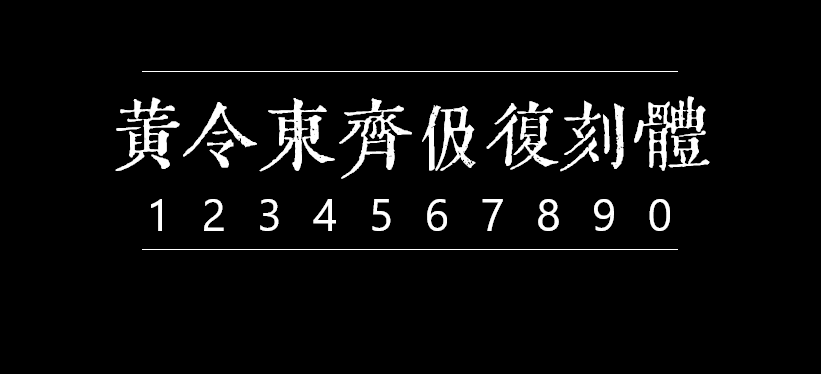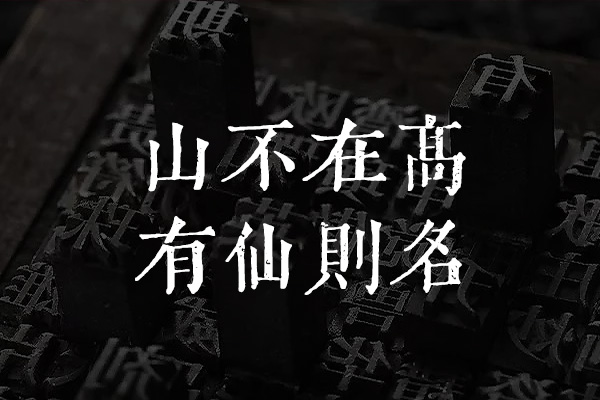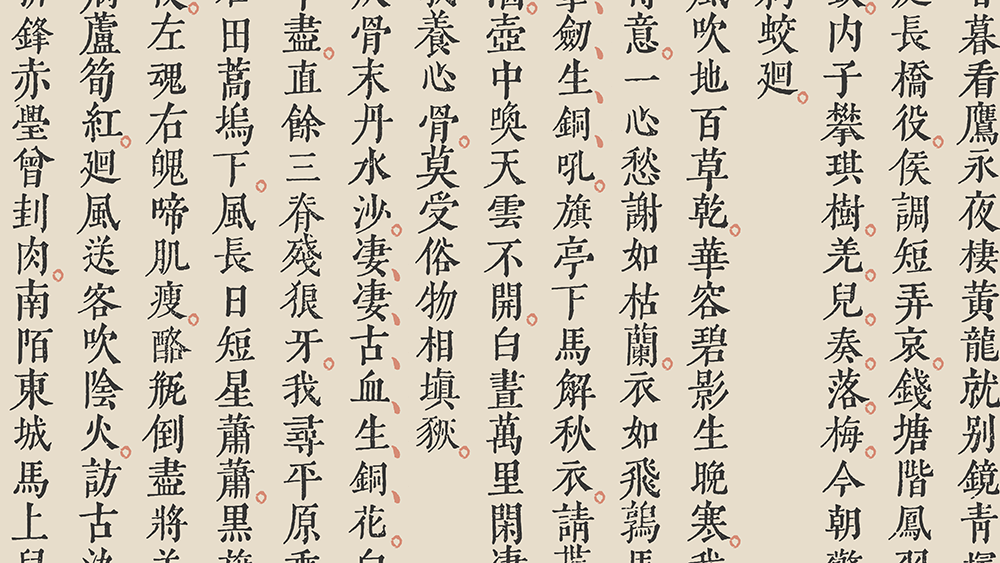
字体下载 黄令东齐伋复刻体
黄令东齐伋复刻体
黄令东齐伋体有两个版本的,一个是Combo版,一个是Fallback版。Fallback版即黄令东齐伋体,Combo版为黄令东齐伋复刻体。 黄令东齐伋复刻体采用半自动计算机视觉和OCR对《李長吉歌詩》和《淮南鴻烈解》进行扫描,在扫描完字体之后,再从中挑选合适合的字形进行微调处理,最后再把结果输出为字体文件。 黄令东齐伋复刻体(QIJC-combo)是对古籍进行处理而得到的字体,所以只有繁体字形。在使用字体的过程中,如果输入简体字会直接映射成繁体字形。比如说你输入“汉”字,出来的结果会是“漢”字。这个结果不难理解,古人不会写简体字。 黄令东齐伋复刻体包含5916个字符,依据SIL Open Font License 1.1授权协议,可以用于任何用途,包括免费商用。